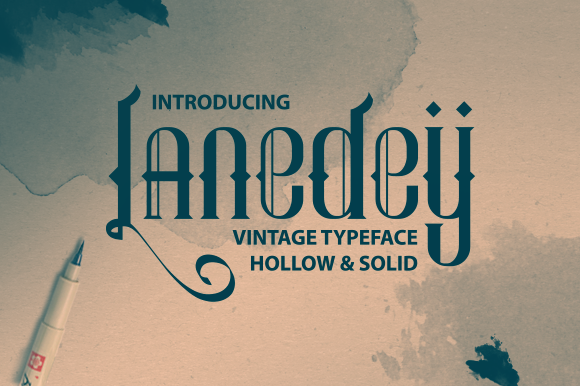
Lanedey Typeface – Download Grátis
A Lanedey Typeface é uma tipografia Display para quem busca uma combinação elegante de modernidade e personalidade. Essa fonte é perfeita para trabalhos que exibem a individualidade do seu design, seja em sites, revistas ou publicações digitais. Com linhas levemente afiadas e tons sóbrios, a Lanedey proporciona um contraponto suave às imagens visuais de seu conteúdo. Ideal para headlines e títulos importantes na sua página web ou impressão, ela é uma escolha excelente para transmitir a identidade visual de seus projetos. Em um mundo digital cada vez mais vibrante e diverso, essa fonte se destaca pela sua capacidade de destacar o estilo único do seu trabalho, sem perder a essência profissional.